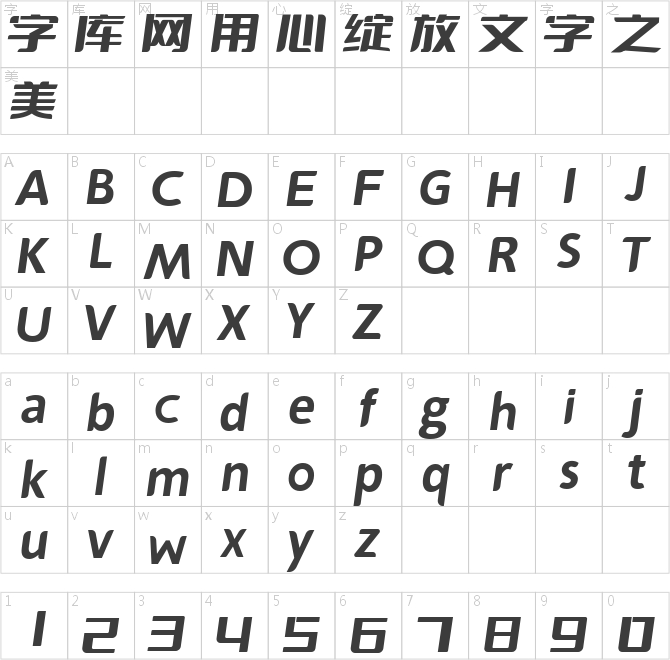
斗鱼追光体 详情页
字体名称: 斗鱼追光体
斗鱼追光体介绍
斗鱼追光体,是由斗鱼武汉研发部UED提供指导,品牌组设计成员主导设计的全新品牌字体。很多人会问,斗鱼为什么要设计自己的字库,我们并非心血来潮,作为一个在国内知名的直播平台公司,我们需要统一的字体来发声,来表现企业自身的风格,并且向外界传递我们自己的品牌特质。我们也想统一公司内所有的子品牌标志与各项目的宣传形象,在视觉上用同一种声音来凸显斗鱼。我们希望用户想到斗鱼公司时,是会联想到一个具有活力、上进,且具有娱乐性质的科技型公司。我们设计团队也是秉承着这些,来设计这套字体。